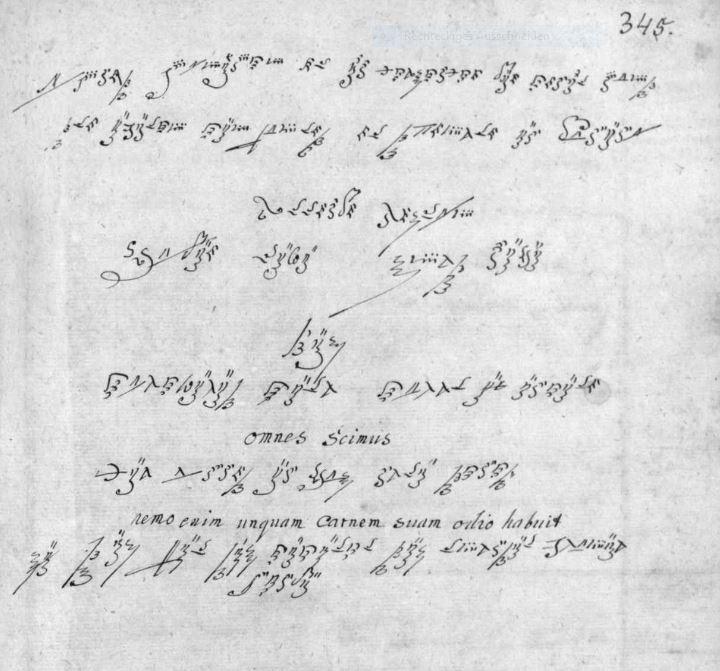
Unbekannte Schrift aus Kirchenbuch ca 1699
Bei meiner Ahnenforschung bin ich in der Trauungsmatrike von Bad Goisern/Österreich 1667-1699 auf folgende Seite gestoßen.
In unserm Forum Ahnenforschung kann mir leider keiner weiterhelfen, es gibt nur Gedanken ob das eine unbekannte Schrift ist oder vielleicht eine Geheimschrift, vielleicht ein Code (Kryptografie fällt mir da ein).
Ein Gedanke dazu: zitiert
Mein ehemaliger Religionslehrer konnte neben Latein und Altgriechisch, die hebräische und arabische Schrift lesen und schreiben. Das würde bedeuten, ein gebildeter Schreiber jener Zeit konnte bzw kannte jene Schriftzeichen auch. Er könnte daher aus diesen Alphabeten zu seinen Zeichen inspiriert worden sein. Manche erinnern auch an Glagolithisch
Geschrieben wurde offensichtlich von links nach rechts. Der Text enthält mehr als 26 unterschiedliche Zeichen → es gibt Konsonanten und Vokale, eventuell auch Ziffern, Ligaturen und Abbreviaturen etc.
Hebräisch schließe ich daher aus (wozu auch verschlüsseln?)
2mal kommen Zeichen als Doppelvokal oder -konsonant vor. Das gibt es im Deutschen und in welcher Sprache noch?
Vielleicht kann mir aus diesem Forum wer helfen, wär natürlich ein Erfolg, auch wenn raus kommt das es nur Nonsens ist.
Beim ersten Hinsehen musste ich an eine Notation ähnlich der Neumen denken ... mir fehlt aber leider fundiertes Wissen – und außerdem gerade die Zeit, da nachzuforschen. Aber vielleicht lohnt es sich doch, in dieser Richtung mal nachzudenken?
die Entschlüsselung solcher Schriften ist ganz sicher zeitraubend.
Ich bin mir ziemlich sicher, dass es zumindest in Teilen der griechischen Sprache entlehnt ist. Das dritte Wort kenne ich als nomen sacrum für κύριος. Ich meine auch verschiedene λ, ξ und η zu erkennen, doch das mag nicht viel heißen. Vielleicht hilft Dir ja der Capelli weiter: https://archive.org/details/LexiconAbbreviaturarum
Ich glaube nicht, dass das eine "Geheimschrift" ist. Es sieht mir nach einer Notiz in einer Handschrift aus, die aus einer Zeit stammt, in der weder Schrift noch Orthographie in einem nachvollziehbaren Maß standardisiert war. Ich bin mal über einen Thread gestolpert, in Nutzer die Einkaufszettel von griechischen Omas zu entziffern suchten. Da waren, trotz Muttersprache, einige Wörter schlicht nicht lesbar aufgrund höchst individueller Ligaturen.
Ich dachte zuerst, daß es sich vielleicht um eine Art Kurzschrift handelt, aber dazu sind die Zeichen wohl zu kompliziert, und auch falsch angeordnet. Welche Sprachen außer Latein und Griechisch hätte der durchschnittliche Kleriker dieser Zeit beherrscht? Aramäisch und Syriac sehen ja anders aus.
Die glagolitische Schrift war auch 1670 noch im Kirchen-Gebrauch, aber sehr regional. Wobei Bad Goisern ja schon fast Istrien ist … ;-)
Zunächstmal ist die Frage, ob es sich überhaupt um a) die Notation einer Sprache; b) um eine Art alphabetische Schrift handelt. Das ist nicht sofort zu beantworten, mir kam auch gleich der Gedanke, daß es sich evtl. auch um eine Art Musiknotation handeln könnte. Wirkliche Anhaltspunkte sehe ich dafür aber nicht, genausowenig wie für Glagolitisch, Hebräisch oder was sonst noch (voreilig?) erwähnt wurde.
Ich habe Glagolitisch nicht voreilig erwähnt, als mögliche Lösung des Rätsels schon gar nicht, sondern als Antwort auf die Frage "Welche Sprachen außer Latein und Griechisch hätte der durchschnittliche Kleriker dieser Zeit beherrscht?" gegeben.
Ehrlich gesagt bin ich schon mit der Fülle an "Noten, Schriften, usw... überfordert.
Aber es ist schon erstaunlich dass in mitten alter Kurrentaufzeichnungen völlig "unmotiviert" so ein Text erscheint.
Hab mir mal alle Links und Hinweise angesehen, auch den Capelli. Leider auf die Schnelle nichts Vergleichbares gefunden.
11. MUNDI / der Welt.
Die Schrift ist zumindest dem Internet völlig unbekannt. Ich musste also praktisch bei Null anfangen.